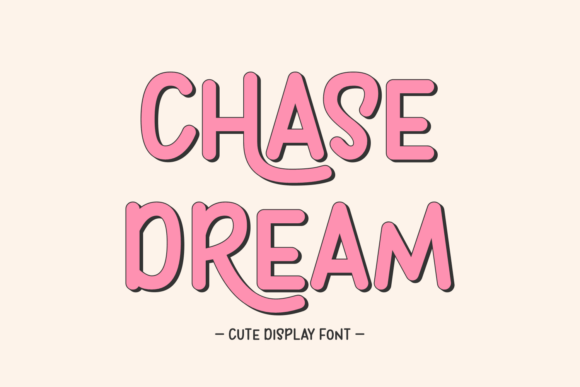
Chase Dream
إذا كنت تبحث عن أصول عالية الجودة مثل Chase Dream، فإن هذه الحزمة المميزة هي خيار رائع لمشاريعك الإبداعية.
تم تصميمه بدقة، ويوفر Chase Dream متجهات نظيفة وطباعة سلسة وترخيصًا تجاريًا لراحة بالك.
سواء كنت تقوم بإنشاء منتجات الطباعة عند الطلب أو دعوات الزفاف أو رسومات وسائل التواصل الاجتماعي، فإن Chase Dream هو الخيار المثالي.